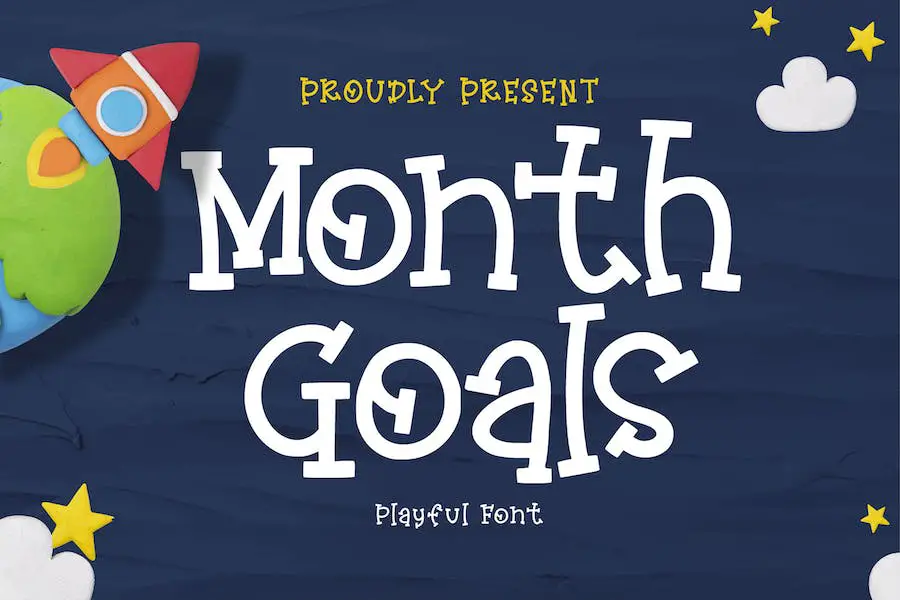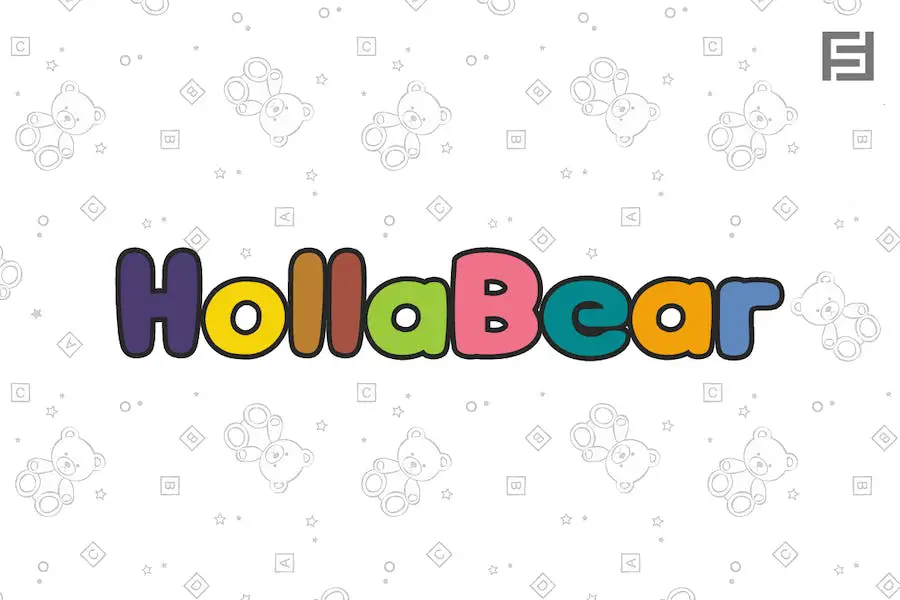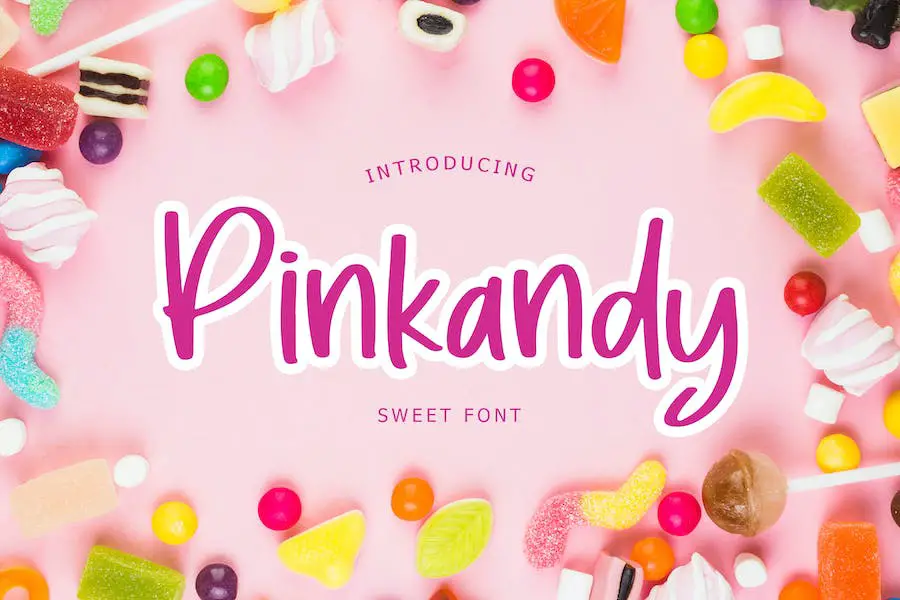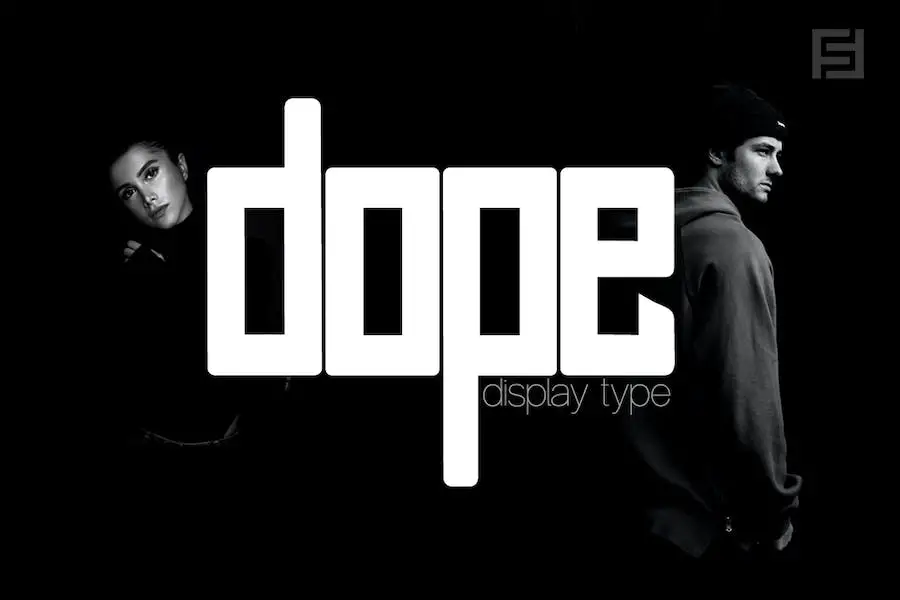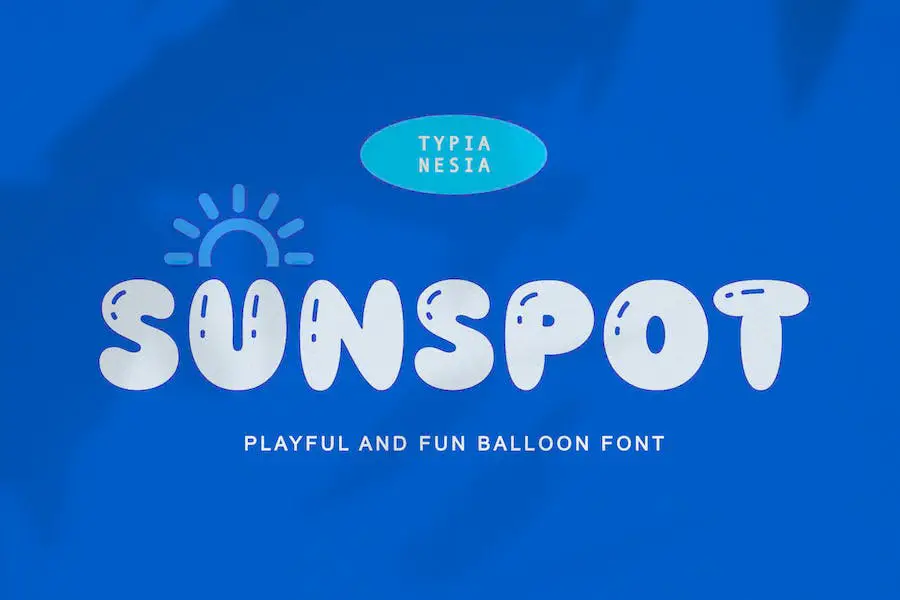
15 meilleures polices Meme 2023 (gratuites et premium)
Publié: 2023-07-30Êtes-vous un graphiste à la recherche de la police parfaite pour améliorer la conception de votre projet ? Cherchez pas plus loin! Dans cet article de blog, nous discuterons des 15 meilleures polices meme qui feront passer vos créations au niveau supérieur.
Mais vous vous demandez peut-être pourquoi les polices meme? Ne sont-ils pas juste pour l'humour sur Internet ? Eh bien, laissez-moi vous assurer que les polices meme ont évolué pour devenir un choix populaire parmi les graphistes en raison de leur polyvalence et de leur capacité à ajouter une touche ludique et tendance à n'importe quel design.
Maintenant, avant de plonger dans le monde des polices meme, prenons un moment pour apprécier l'impact et la popularité qu'elles ont acquis ces dernières années. Les polices Meme font désormais partie intégrante de la culture Internet et se répandent comme une traînée de poudre sur les plateformes de médias sociaux.
Leurs styles uniques et accrocheurs les ont rendus très recherchés par les designers et les amateurs de mèmes.
En fait, selon des enquêtes récentes, les polices meme ont vu leur utilisation augmenter de 50 % chez les graphistes, ce qui en fait un sujet brûlant dans la communauté du design.
Dans cet article, nous vous présenterons les 15 meilleures polices de mèmes qui ont suscité des critiques élogieuses parmi les concepteurs et ont joué un rôle déterminant dans la création de mèmes viraux.
De l'impact classique et intemporel de la police Impact au Comic Sans fantaisiste et ludique, nous explorerons une gamme de polices qui apporteront personnalité et humour à vos créations.
Ainsi, que vous travailliez sur une affiche inspirée des mèmes, un graphique de médias sociaux ou que vous souhaitiez simplement injecter du plaisir dans vos projets de conception, ces polices de mèmes inspireront et élèveront sans aucun doute votre créativité.
Alors sans plus tarder, commençons ce voyage font-tastic !
Meilleures polices Meme Premium
Vous cherchez à élever votre jeu de mèmes ? Ne cherchez pas plus loin que ces polices premium qui ajouteront à coup sûr une touche d'humour et de personnalité à vos projets. Ne manquez pas l'occasion d'explorer ces polices incontournables !
Franck drôle
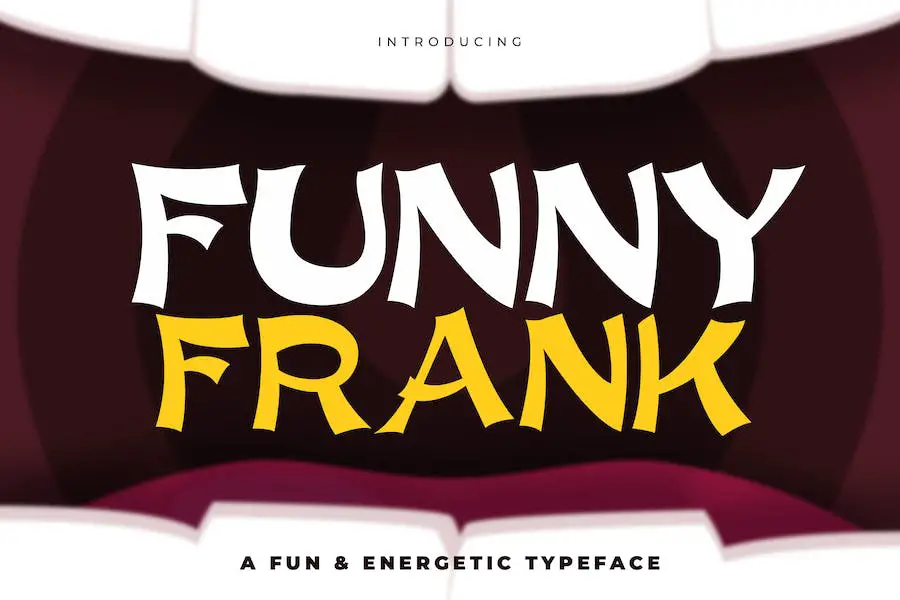
Funny Frank est une police qui ajoute de l'humour et de l'espièglerie à vos projets de conception. Il est polyvalent et fonctionne bien avec d'autres polices de caractères, ce qui le rend parfait pour les conceptions de t-shirts et de produits.
Que vous créiez un slogan original ou un titre audacieux, Funny Frank ajoutera une touche supplémentaire de plaisir. Alors allez-y, laissez libre cours à votre créativité et faites rire vos créations avec Funny Frank.
Rotterdam
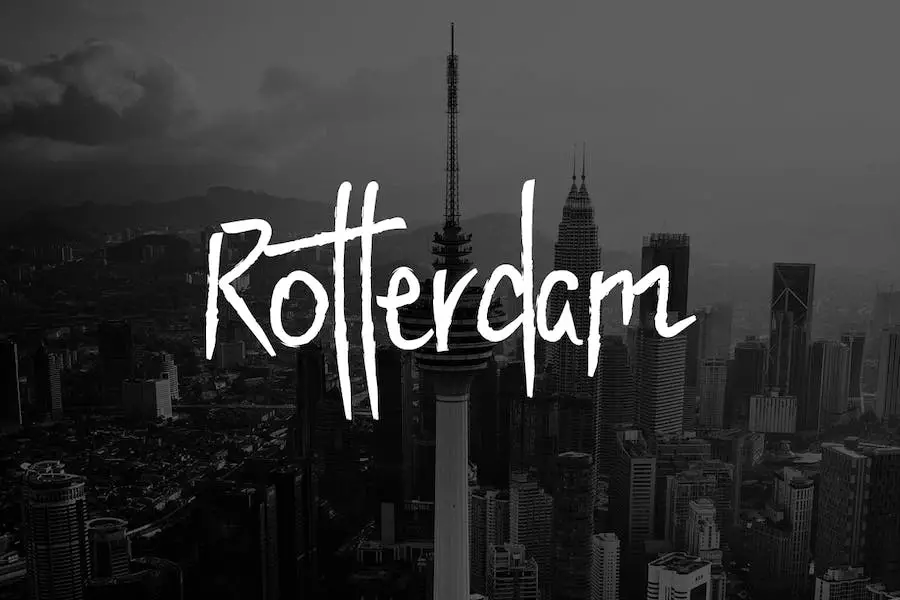
Rotterdam est une police manuscrite unique, parfaite pour améliorer tout projet de conception. Que vous travailliez sur l'affichage, l'image de marque, le logotype, les conceptions d'emballages, les conceptions de panneaux d'affichage, les affiches ou même les mèmes et les graphiques de médias sociaux, cette police est le choix ultime.
Inspiré du graffiti urbain, il présente un design de pinceau personnalisé qui ajoute une touche de chic urbain à vos créations.
L'une des caractéristiques les plus remarquables de Rotterdam est son crénage avancé. Les créateurs de cette police ont méticuleusement ajusté l'espacement entre les lettres pour garantir que chaque combinaison de lettres soit impeccable.
Blob amusant
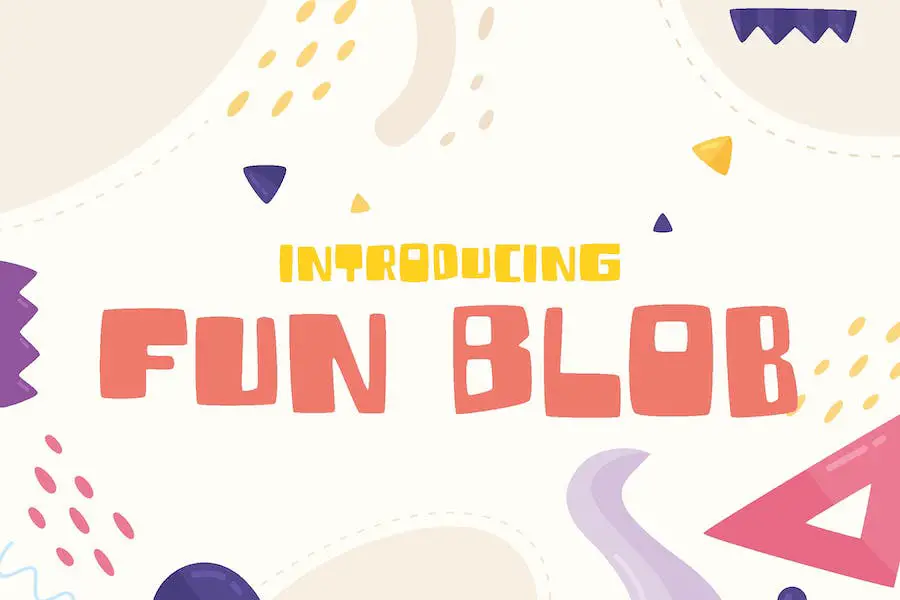
Fun Blob est une police qui ajoutera une touche de fun et de personnalité à vos créations. Avec ses coins arrondis et sa forme originale et joyeuse, cette police ne manquera pas de faire sensation.
Il est parfait pour une variété de projets, des jeux en ligne aux affiches, des menus de restauration rapide de titres de films et même des mises en page de magazines. Vous pouvez également l'utiliser pour vos couvertures YouTube, vignettes, publications Instagram et autres conceptions de couverture de médias sociaux.
Monde de craie
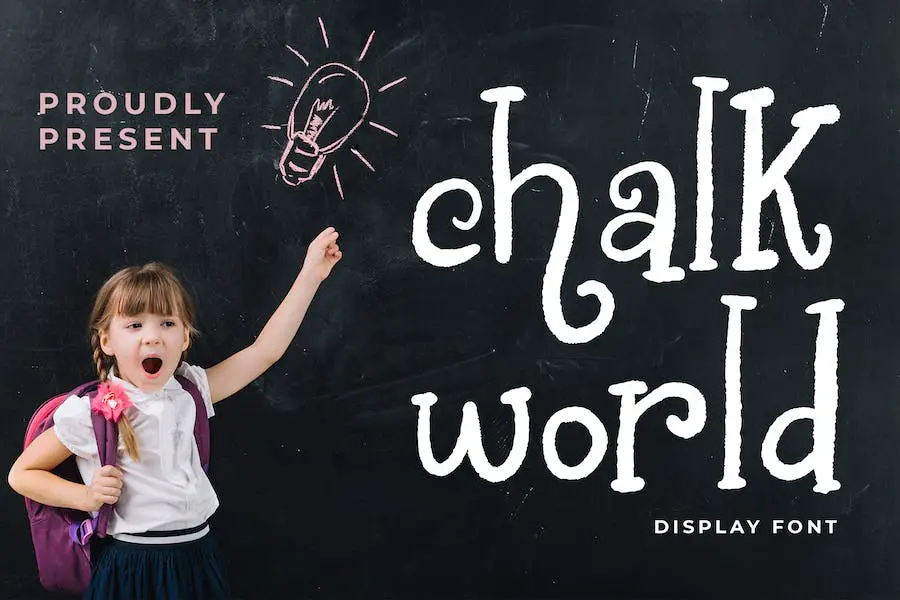
Chalk World est une police d'affichage ravissante et captivante qui ajoute une touche de charme à la conception thématique de tout enfant.
Il est parfait pour une variété de projets créatifs, y compris l'image de marque, la conception de logos, les couvertures de livres, les conceptions de t-shirts, les publications sur les réseaux sociaux, les publicités, les emballages de produits, les étiquettes, les invitations et la papeterie.
Avec son style mignon et ludique, Chalk World se démarque et capte l'attention sans effort. Cela apporte une touche de fantaisie et de plaisir à vos créations, les rendant plus engageantes et mémorables.